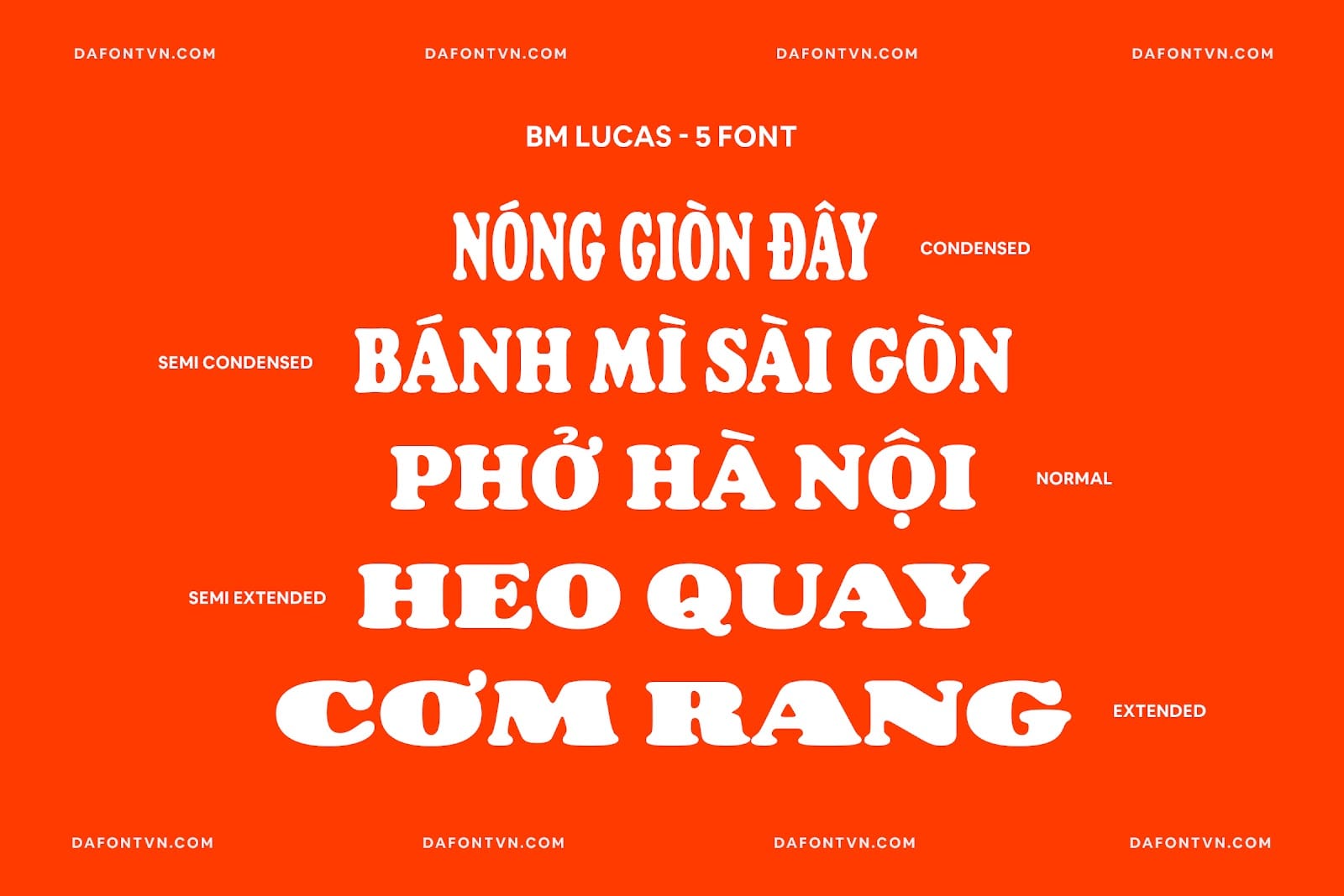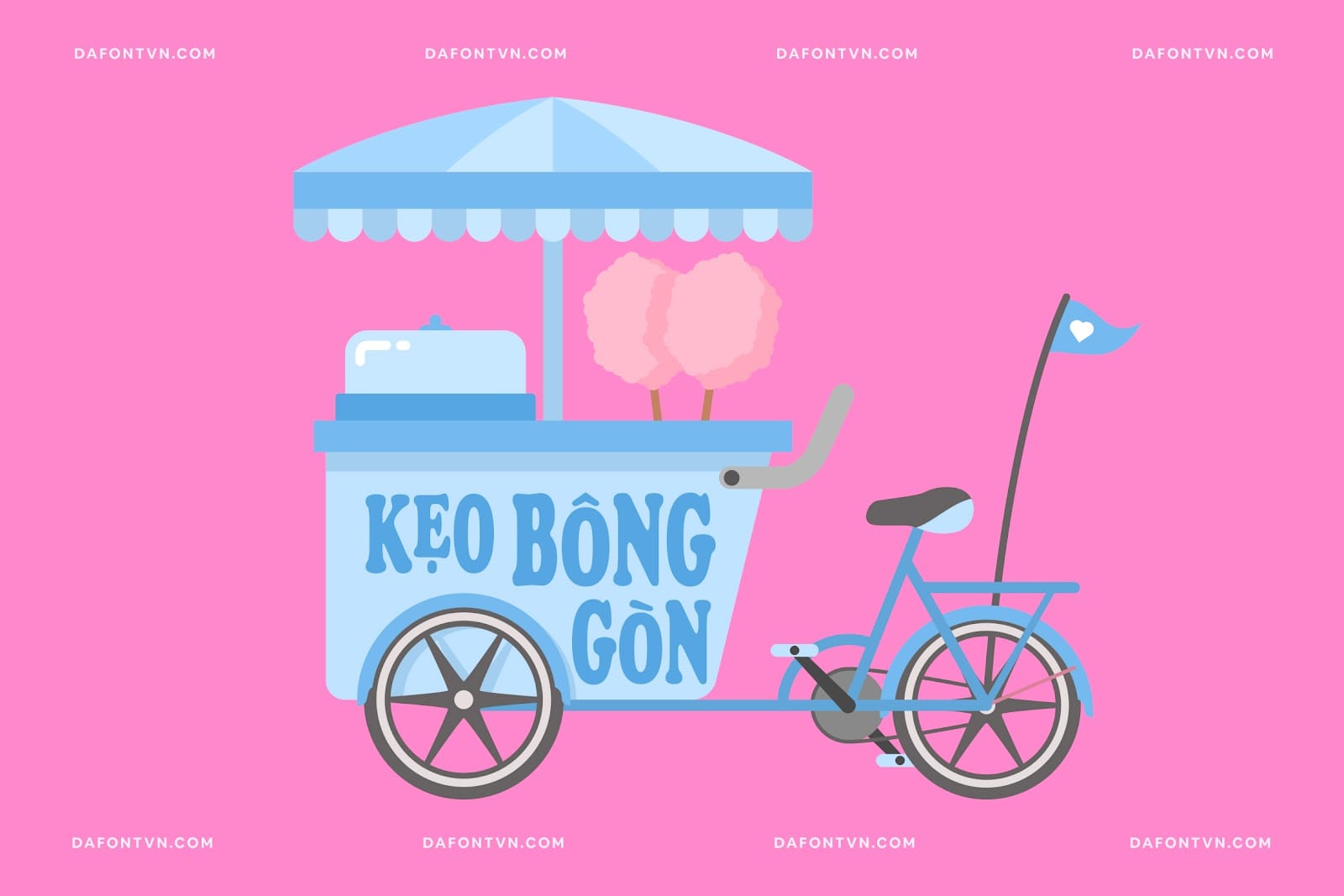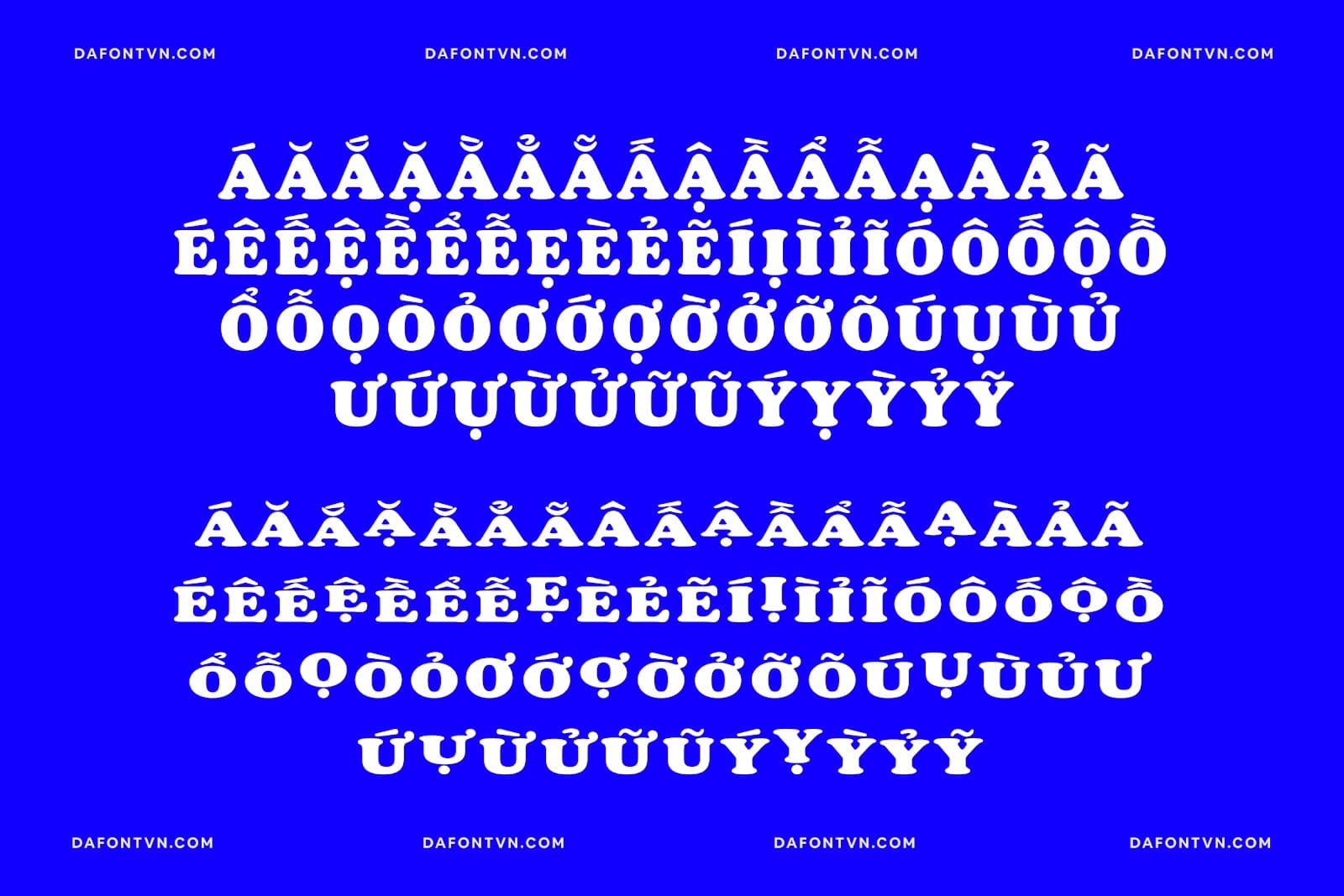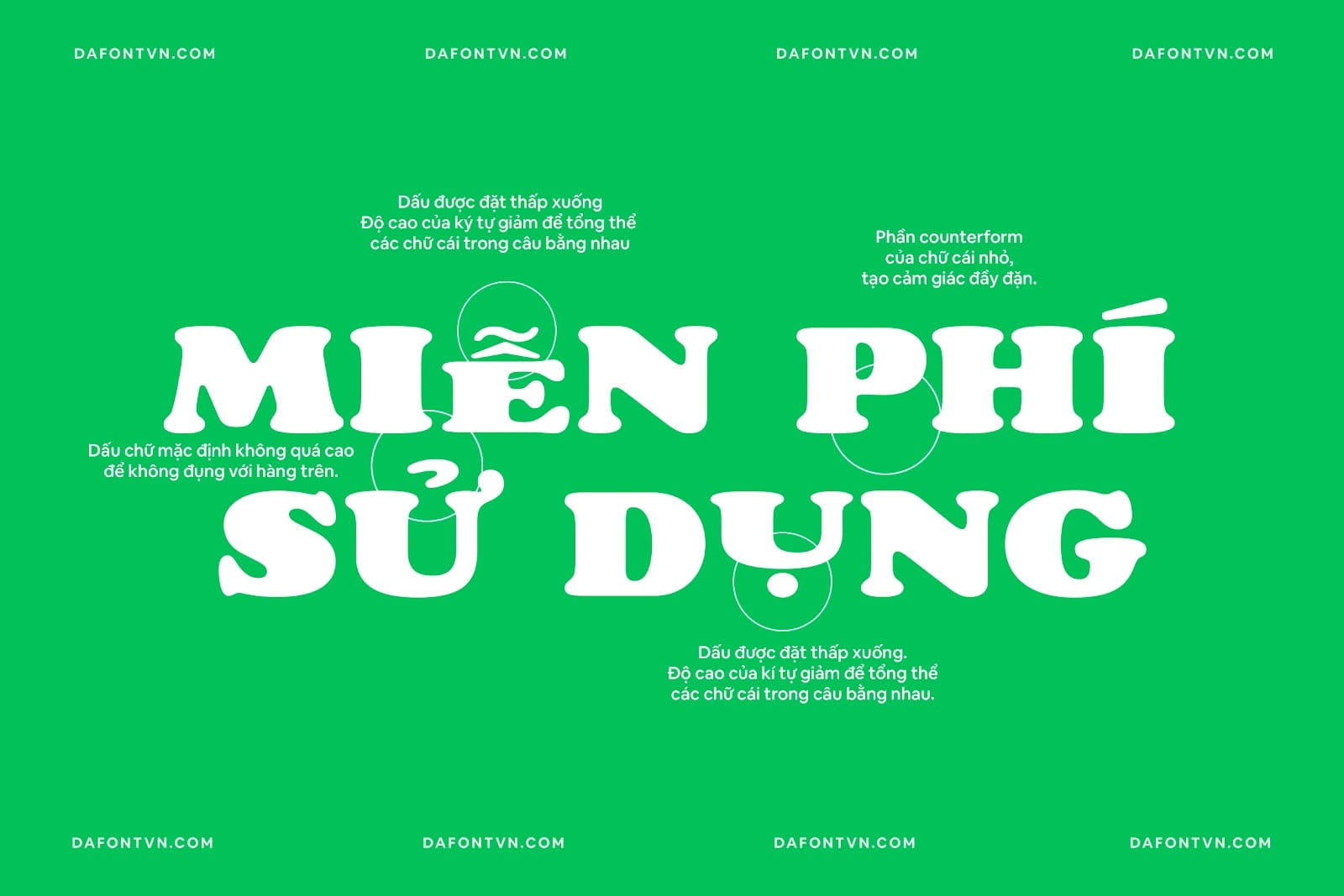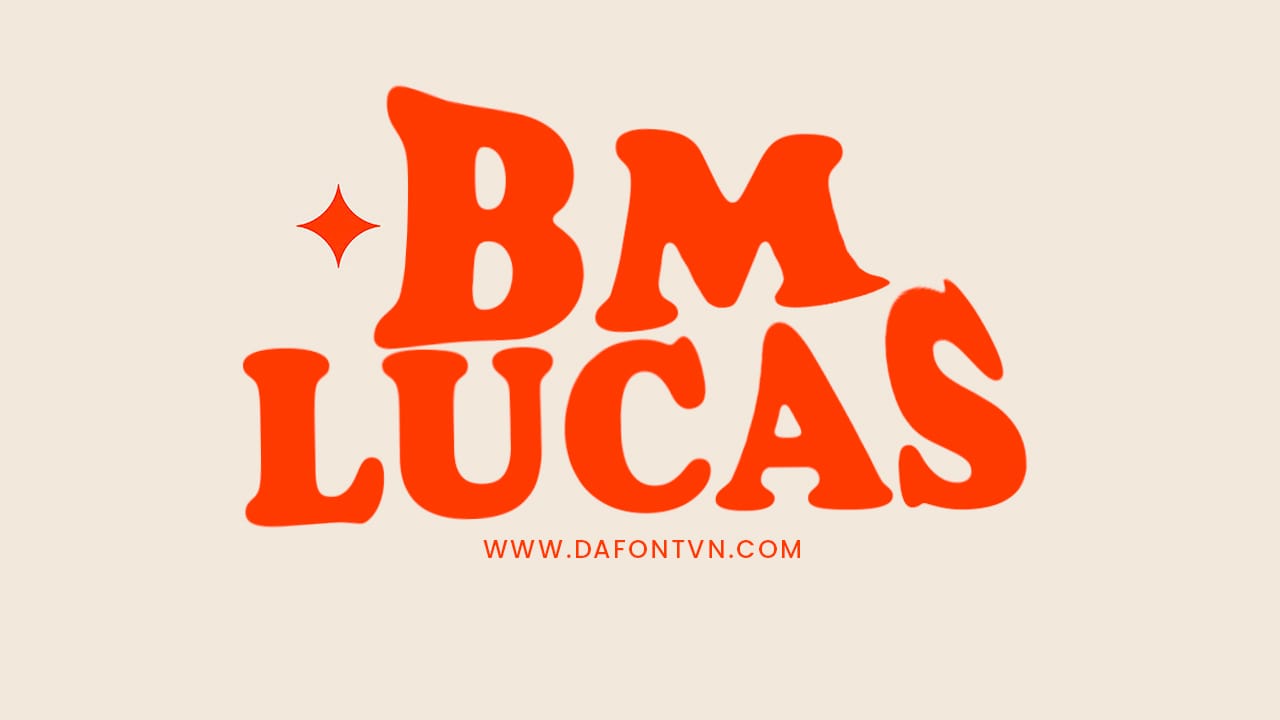
BAEMIN vừa cho ra mắt bộ phông chữ mới mang tên
BM Lucas , bộ font được lấy cảm hứng trên bộ phông chữ cổ điển Cooper Black và được tùy biến cũng như dễ dàng tùy chỉnh thiết kế theo ý thích của mình.
Bộ font BM Lucas mang phong cách ẩm thực đường phố Việt Nam với 5 kiểu chữ khác nhau. Với chân chữ đậm, hình dạng tròn trịa tạo nên cảm giác có trọng lượng lớn, với độ tương phản giữa các nét dày – mỏng, dạng chữ được thổi phồng tạo dáng vẻ thân thiện, mềm mại, dễ đọc và cũng rất ấn tượng.
BM Lucas là bộ phông chữ thứ 2 của BAEMIN, trước đó bộ phông chữ
đã được giải thưởng Type Champions Award 2020 cùng giải thưởng cao nhất “Best of the Best” ở hạng mục Thương hiệu và Thiết kế Truyền thông tại Lễ trao giải Red Dot Awards 2021.